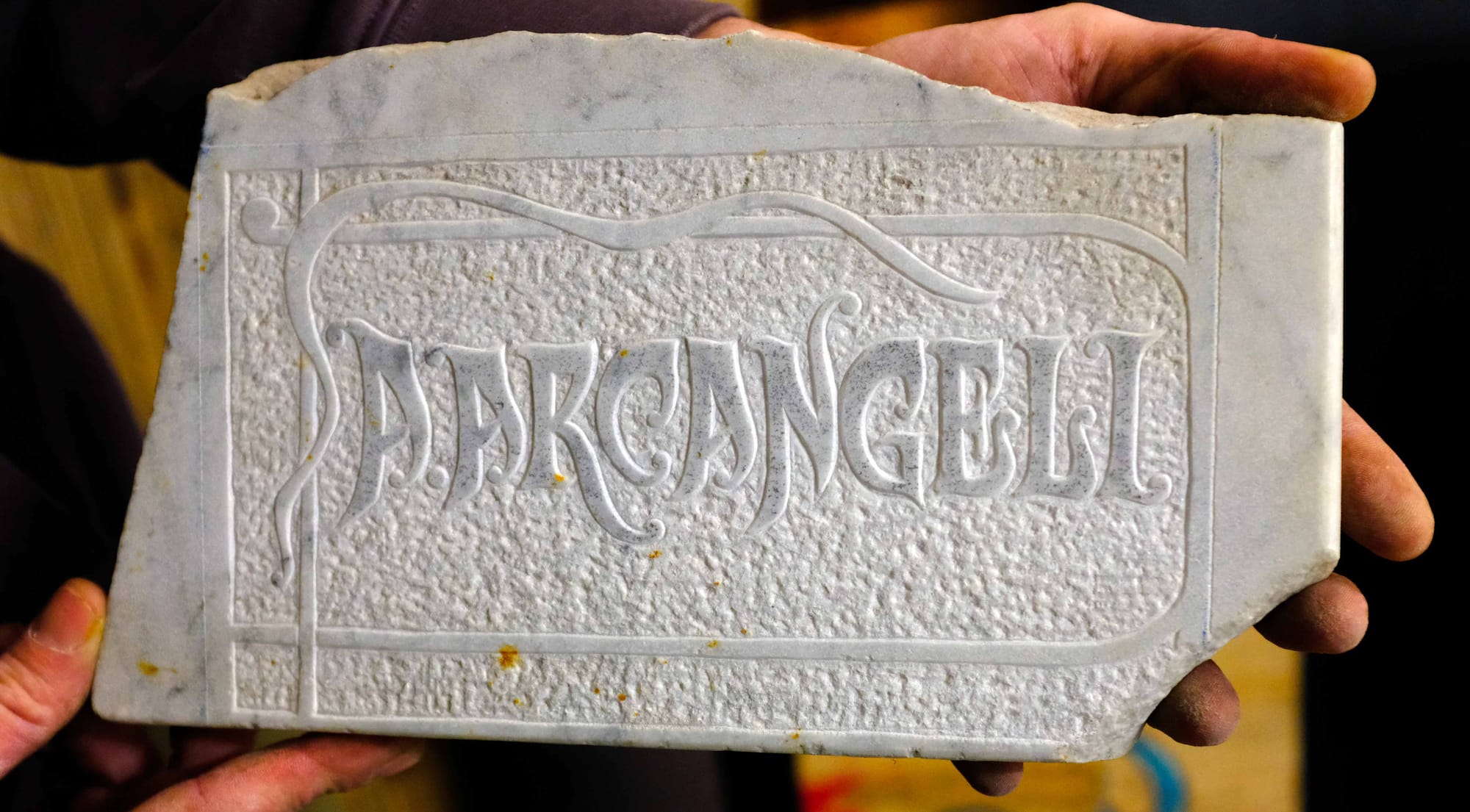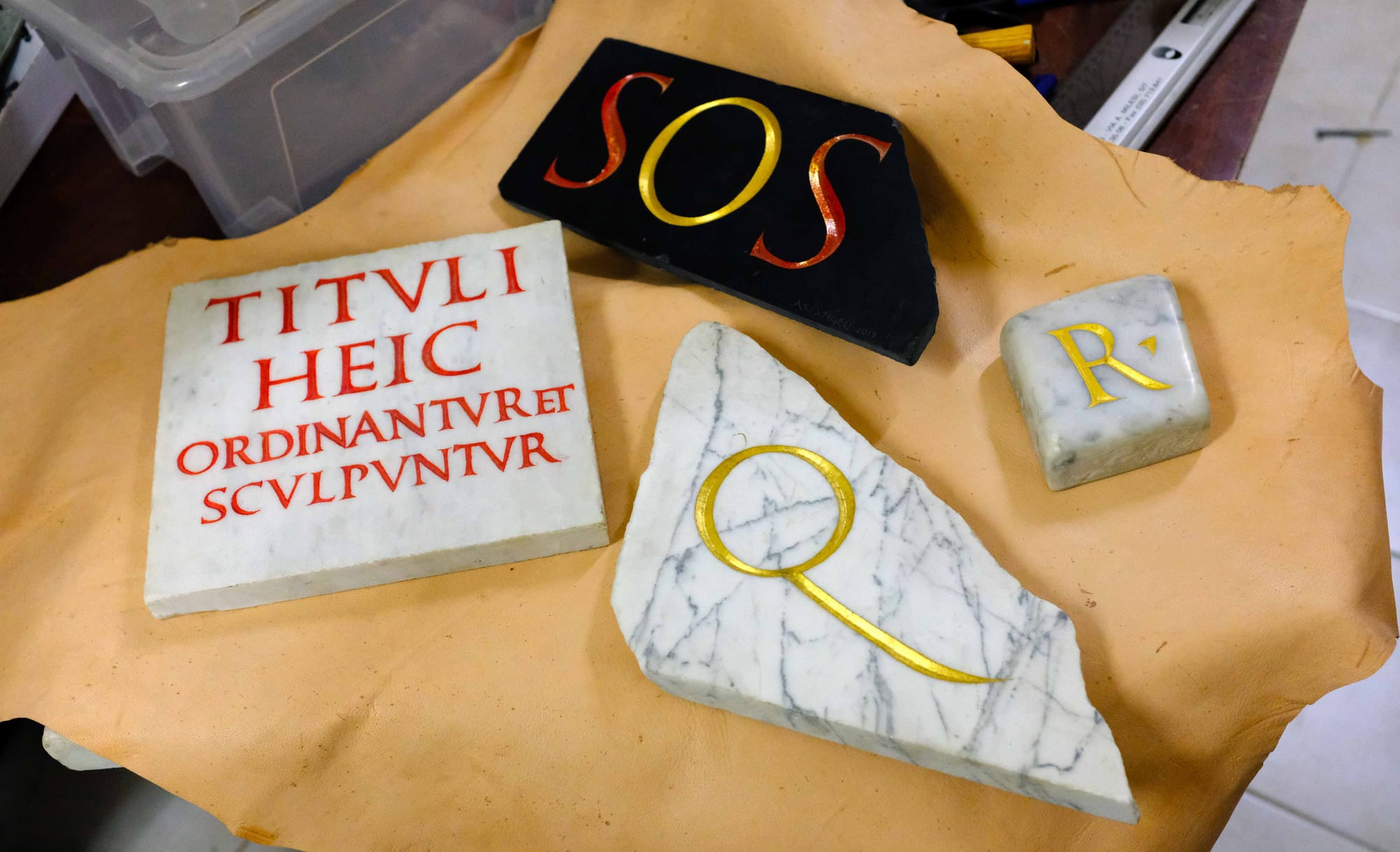
Ars longa: la necessità di voler lasciare un segno
La prima volta che ho stretto la mano di Andrea Arcangeli siamo entrati subito in sintonia. Ed era una questione tutt'altro che secondaria: di lì a poco avremmo tenuto insieme una lezione davanti a un gruppo di studenti universitari della RUFA, a Roma. Fino a quel momento ci eravamo parlati solo al telefono, separati dai chilometri ma accomunati dalla stessa passione per le lettere e per la loro storia.
L'idea di invitare Andrea a eseguire una dimostrazione dal vivo di diversi stili calligrafici mentre io ne raccontavo il contesto storico mi era sembrata del tutto naturale. Solo dopo mi resi conto che, in fondo, stavamo andando molto a intuito, fidandoci l'uno dell'altro: non ci eravamo mai incontrati di persona e ci conoscevamo soprattutto attraverso i social. Eppure avevamo entrambi la sensazione che avrebbe funzionato. Bastarono pochi minuti per capire che quella sensazione era giusta.
Da allora sono passati diversi anni e la nostra amicizia si è fatta sempre più solida, accompagnata dall'ammirazione che provo per il suo percorso artistico che, partendo dalla calligrafia, ha trovato espressione in molti altri ambiti: l'incisione lapidaria, la scultura, la ricostruzione storica, l'artigianato e lo studio delle tecniche e della cultura del mondo antico.
Da tempo desideravo intervistarlo. Così sono andato a trovarlo nel suo studio romano, armato di macchina fotografica e di curiosità. Abbiamo trascorso insieme una giornata fatta di racconti, osservazioni e divagazioni, senza seguire una traccia precisa. Abbiamo parlato di lettere, di storia, di strumenti, di maestri e di artigianato; abbiamo pranzato in un'osteria romana e poi siamo tornati nel suo laboratorio, circondati da pietra, inchiostro e oggetti che sembrano appartenere a epoche diverse ma convivono armoniosamente nello stesso spazio.
Qualche giorno dopo gli ho inviato cinque domande. Le risposte di Andrea restituiscono il ritratto di un artista che non si limita a praticare una disciplina, ma ne indaga continuamente le radici, i significati e le trasformazioni. Un percorso che attraversa secoli di storia e che trova nella lettera — scritta, incisa o scolpita — il proprio filo conduttore.
Quando è stata la prima volta che hai preso in mano uno strumento calligrafico e perché avevi sentito la necessità di farlo?
La prima volta che ho usato uno strumento calligrafico è stato a casa di mia nonna, avevo circa dodici anni e lei tirò fuori una vecchia scatola piena di materiali da cancelleria d’una volta; mi raccontò di quando insegnava Educazione Tecnica e Calligrafia, tra le materie scolastiche di un tempo, e di quanto fosse importante saper scrivere bene e in maniera chiara e leggibile. Quello che pareva un semplice gioco con pennino e inchiostro divenne, anni dopo, la base per la mia realizzazione artistica e lavorativa.
Lo studio della calligrafia ti ha spinto a cercare non solo le forme, ma anche il contesto che le ha prodotte. Quando hai capito che non ti bastava più soltanto scrivere bene?
Il mio percorso è iniziato proprio come esponente di un movimento a me contemporaneo che si esprimeva nel contesto urbano dei primi Duemila: quello dei graffiti. L'ho vissuto da "letterista inconsapevole", in quanto mi focalizzavo sulla firma, sul nome, e facevo solo lettere. Intorno ai diciotto anni ho ripreso in mano i pennini che mia nonna mi aveva fatto conoscere tanti anni prima, e ho iniziato una sorta di percorso a ritroso nella storia della scrittura: partendo dalle scritture del Novecento, in particolare dal corsivo inglese, ho poi cominciato a studiare seriamente gli stili calligrafici, passando alle scritture medievali – ed esplorando nel frattempo vari stili ibridi tra graffiti e modelli storici – fino ad approdare alle scritture romane, che mi hanno poi portato a interessarmi non solo di scrittura, ma anche di incisione.
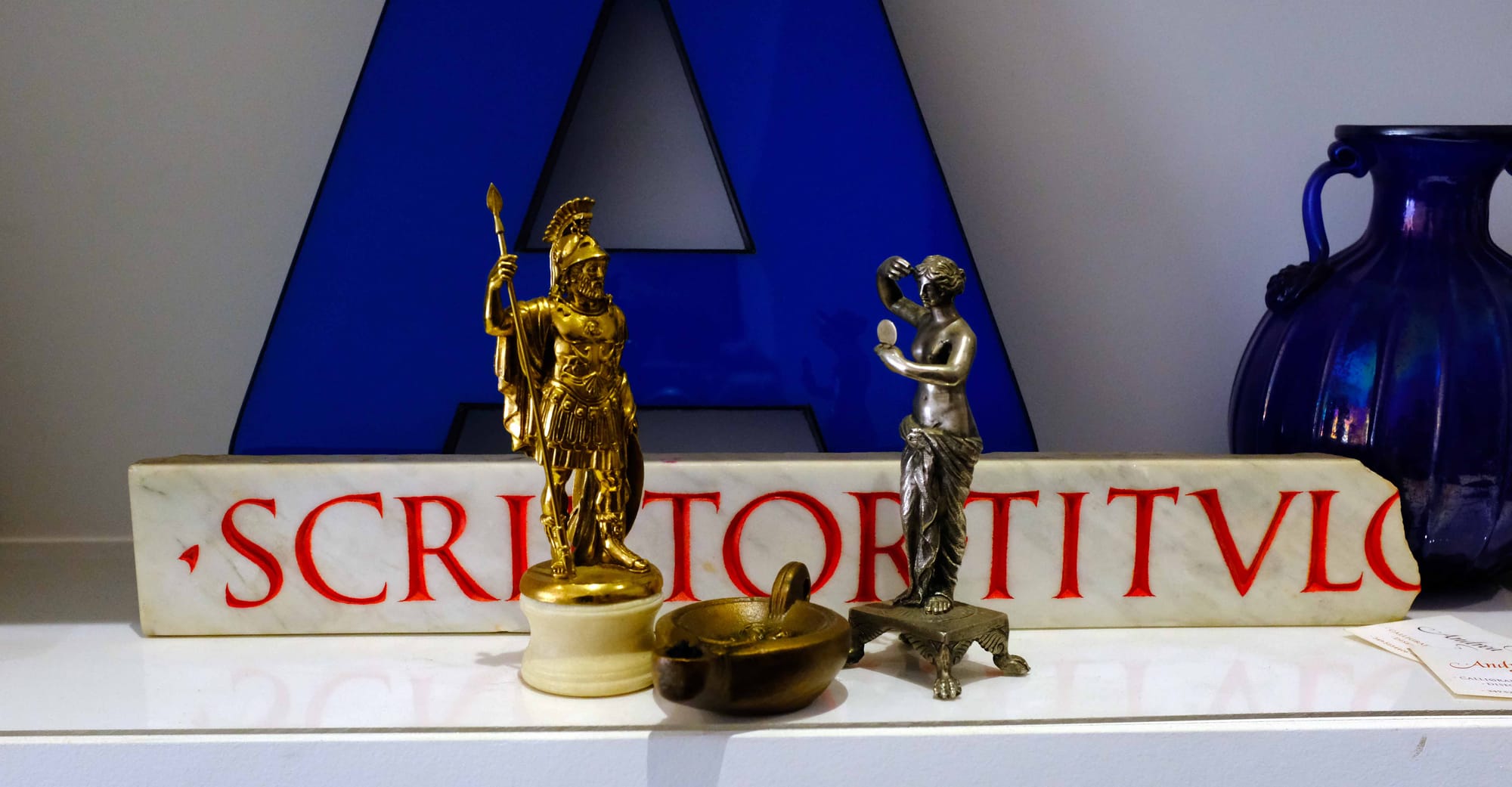
Crescendo ho compreso quanto sia importante avere una forte base culturale e storica in ciò che si fa, soprattutto quando si ha a che fare con tecniche e arti del passato. Un buon calligrafo e una persona che ha approfondito anche la paleografia, che ha cercato di ricostruire il modo in cui si faceva una volta per riproporlo con nuovo slancio e vigore. Saper solo scrivere bene – avere "buon manico", come mi disse il maestro e amico Ivano Ziggiotti – non è l'unica cosa importante nel fare calligrafia: sono lo studio delle scritture storiche e la disciplina della pratica quotidiana a formare un calligrafo che si rispetti.
Più in generale mi reputo una persona curiosa, e questo lo esprimo in vari aspetti della vita. Quando ho capito che la calligrafia era un'arte importante per me, ho voluto approfondirla sotto molti punti di vista, arrivando, oltre allo studio personale di paleografia, epigrafia, filologia e materie affini, a ricostruire strumenti e oggetti legati alla scrittura, a produrre inchiostro ferrogallico da ricette medievali e rinascimentali, a collezionare pennini e manuali d'epoca e tutto ciò che trovavo affine al mio interesse verso l'arte della scrittura.
Tu sei passato dal lasciare una traccia con il segno, al creare un solco nella materia, fino a far riemergere oggetti che non esistevano più. Come senti legati tra loro questi momenti creativi?
Come dicevo prima, sono una persona profondamente curiosa: se c’è qualcosa che stimola il mio interesse e sento che vale la pena approfondire, ci vado fino in fondo. Il percorso, iniziato dai graffiti wildstyle adolescenziali, mi ha portato negli anni fino alla formalità delle scritture classiche incise su pietra e alla ricostruzione di alcuni aspetti della vita quotidiana del mondo classico della Roma Imperiale. Sono, in effetti, ambiti alquanto lontani tra loro! Eppure nascono entrambi dalla necessità di voler lasciare un segno, di rimanere in qualche maniera, cosa che motiva un po’ tutto quel che faccio da sempre.
Saluto Andrea gettando un ultimo sguardo verso le sue creazioni: sono fatte in gran parte di marmo e metallo, eppure, ogni volta che le sfioro, mi sembrano più vive che mai.